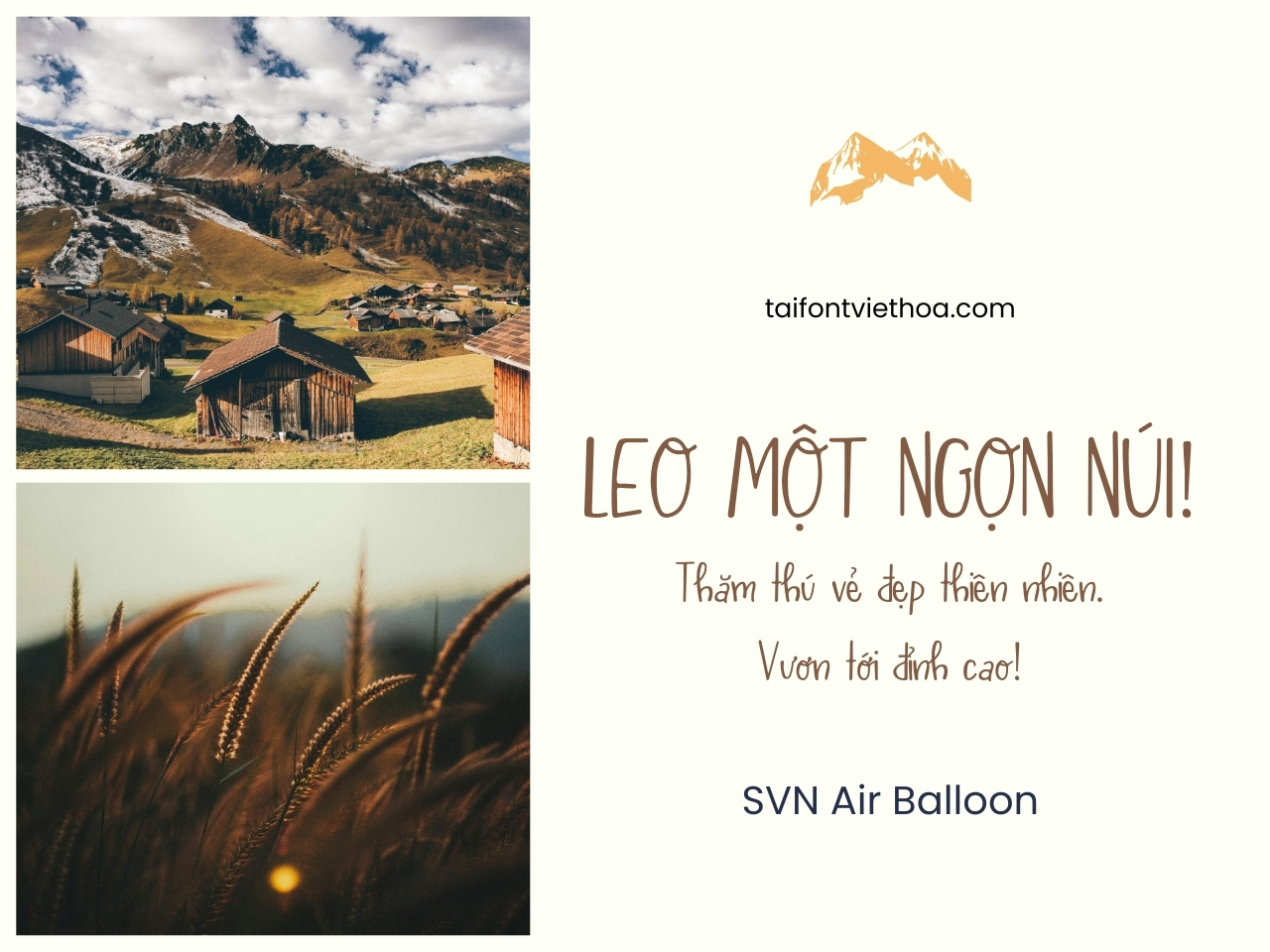
Giới thiệu về font SVN Air Balloon – Kiểu chữ handwritten vui tươi, mềm mại và sáng tạo
SVN Air Balloon là phiên bản Việt hóa của font Air Balloon – một kiểu chữ handwritten mang phong cách vui tươi, mềm mại và rất sáng tạo. Font được thiết kế với các nét chữ uyển chuyển, nhẹ nhàng và biểu cảm, tạo cảm giác gần gũi và thân thiện, rất phù hợp cho các dự án thiết kế thiệp, poster, bài đăng mạng xã hội và các sản phẩm sáng tạo dành cho đối tượng trẻ em và gia đình.
Phiên bản Việt hóa của SVN Air Balloon đã được Taifontviethoa.com chăm sóc kỹ lưỡng, hỗ trợ đầy đủ dấu tiếng Việt cùng hơn 60 ngôn ngữ khác. Font giúp các nhà thiết kế dễ dàng áp dụng trong nhiều dự án sáng tạo mà vẫn giữ được phong cách vui nhộn, đáng yêu và độc đáo.
Thiết kế viết tay mềm mại – Lý tưởng cho thiết kế trẻ em và truyền thông gia đình
SVN Air Balloon sở hữu các nét chữ mềm mại, bay bổng và biểu cảm, tạo nên cảm giác vui vẻ, sinh động và thu hút. Font rất phù hợp cho tiêu đề, thiệp mời, bài đăng mạng xã hội hoặc các phần thiết kế cần sự nổi bật và thân thiện. Phong cách thiết kế của Air Balloon rất thích hợp với các dự án giáo dục, đồ chơi trẻ em, quà tặng và truyền thông dành cho gia đình.
Ứng dụng lý tưởng: thiết kế thiệp, poster, bài đăng mạng xã hội, bao bì sản phẩm và các dự án sáng tạo cần phong cách đáng yêu, thân thiện. Ngành nghề phù hợp: giáo dục, đồ chơi trẻ em, quà tặng, truyền thông gia đình và các thương hiệu định vị theo phong cách vui tươi, thân thiện.